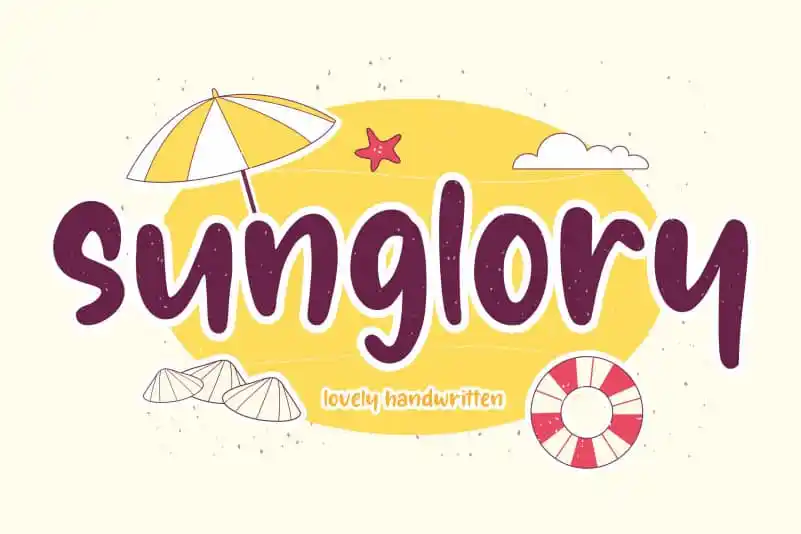
Sunglory Lovely Handwritten Font – Download Grátis
A ‘Sunglory Lovely Handwritten Font’ é uma deliciosa escolha para aqueles que buscam adicionar um toque delicado e autêntico às suas criações digitais. Convidativa aos olhos, esta fonte escrita a mão deixa um sabor suave em qualquer aplicação – seja ela para embalagens de produto, projeto de marca, revistas, mídia social, no estilo de casamento ou simplesmente como forma de expressar ideias acima do fundo. Ideal tanto para elementos visuais dinâmicos quanto para textos sutis, esta fonte é perfeita para qualquer ambiente onde uma escrita delicada e natural seja desejada.